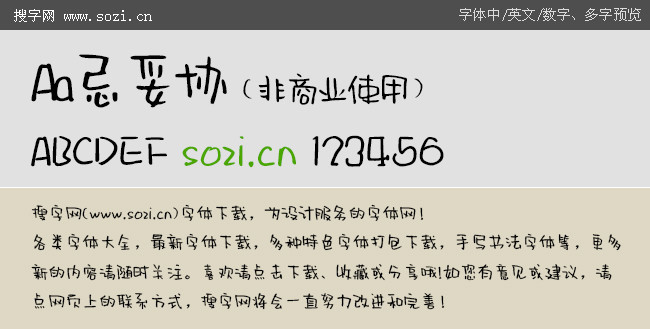
Aa忌妥協(xié)(非商業(yè)使用)
搜字網(wǎng)給大家提供一款A(yù)a忌妥協(xié)(非商業(yè)使用)中文字體下載,該字體是一款手寫中文字體,這款字體可愛,充滿童真,適合包裝設(shè)計(jì)、書裝設(shè)計(jì)、海報(bào)設(shè)計(jì)等應(yīng)用(此字體為個(gè)人非商用版,商用可以聯(lián)系QQ:1006760504)。